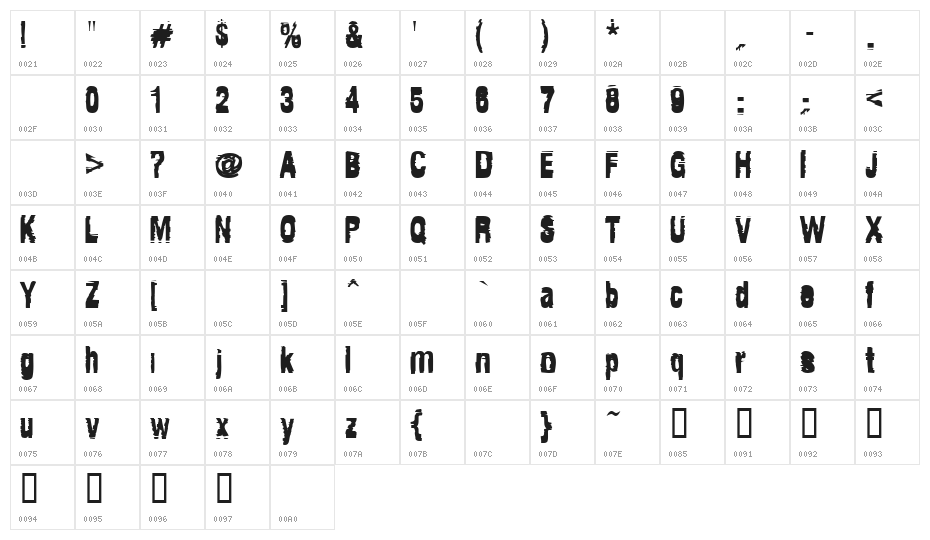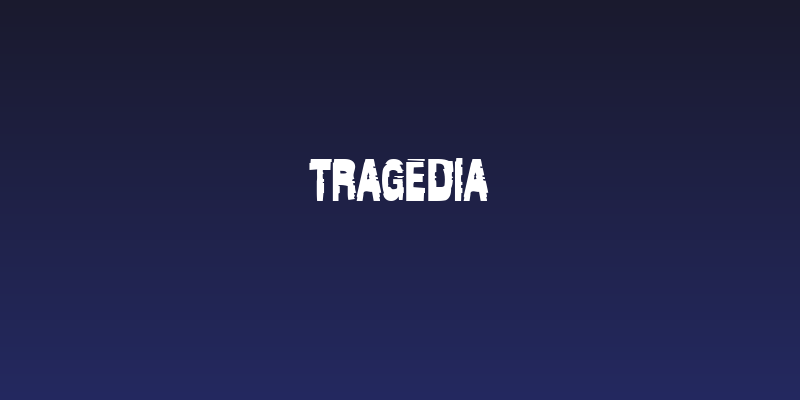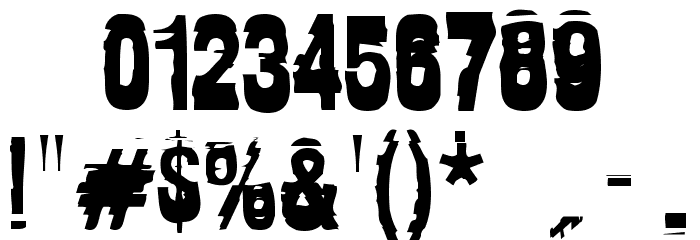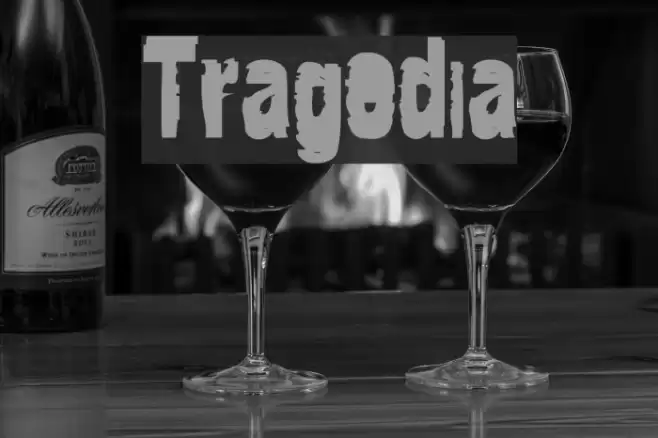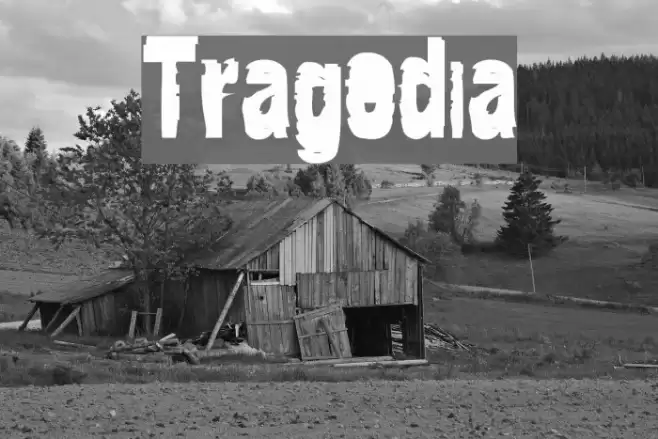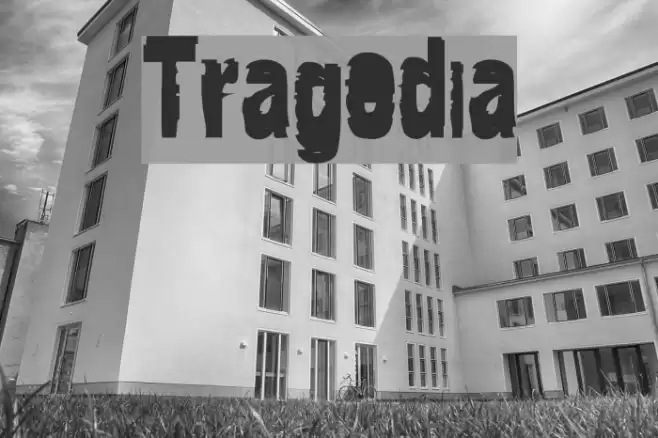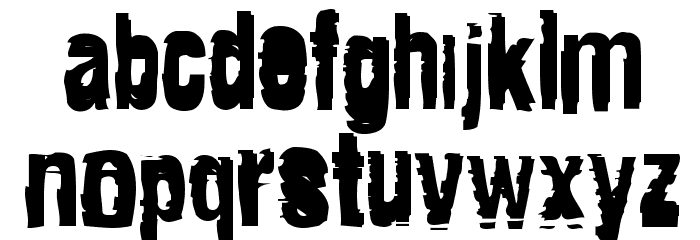
Tragedia Font
| Cas d'utilisation | Headlines, Posters, Logos |
| Projets proposés | Ideal for music album covers, edgy posters, urban-themed designs, and any project needing a dramatic, eye-catching font. |